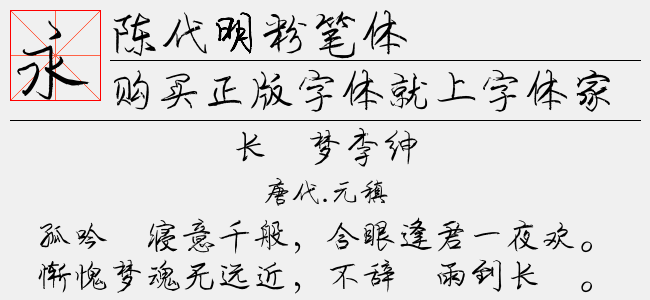
陈代明粉笔字体(8.20 MTTF中文字体下载)
陈代明粉笔字体 字体大小8.20 M,包含了6763个汉字以及附加其他英文字体和阿拉伯数字,属于佚名。陈代明粉笔字体(TTF)可以免费下载,商业用途请自行购买版权,它的特征就是手写,行书,书法,装饰,采用安装嵌入的安装方式,支持符号拉丁文日文中文等语言
字体名称:陈代明粉笔字体